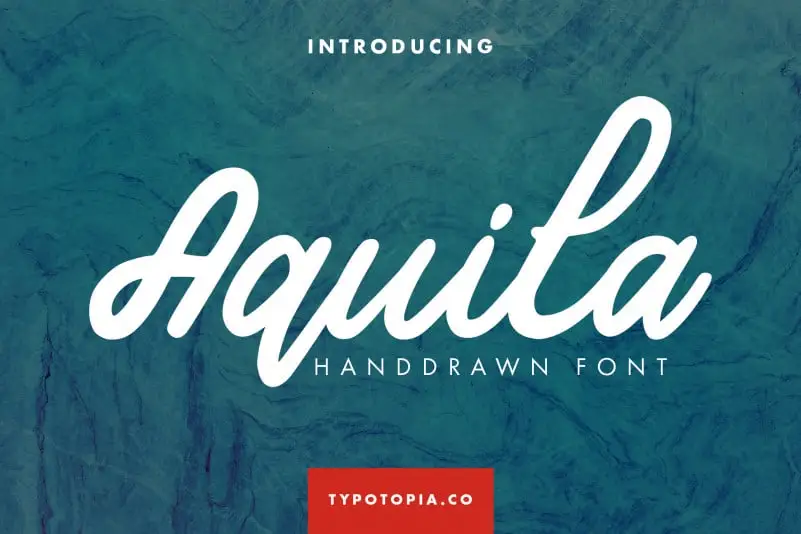
A Aquila Handdrawn Script Font é uma novidade que traz à tona um tipo script com um toque atraente e único. Perfeitamente projetada para quem busca adicionar um toque de sofisticação e personalização aos seus designs digitais, esta fonte irá deixar seu trabalho imprimível ou digital mais encantador. A Aquila não apenas é uma escolha para designers gráficos, mas também para aqueles que desejam enriquecer sua produção com um ar elegante e distinto sem precisar de muito esforço. Se você está procurando por uma fonte script moderna que traz uma pitada de originalidade à cada caractere, então a Aquila é definitivamente o tipo de fonte que você quer ter na sua coleção.